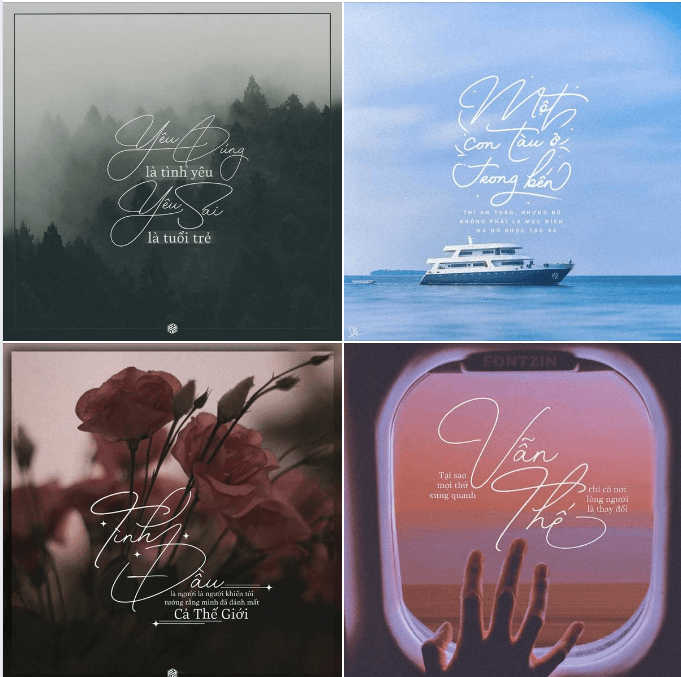
Font The Handwritten Watermark Việt hóa xứng đáng là một siêu phẩm font viết tay, nét chữ được cách điệu kết hợp dạng monoline tạo nên sự thu hút kỳ lạ với bộ phông chữ này.